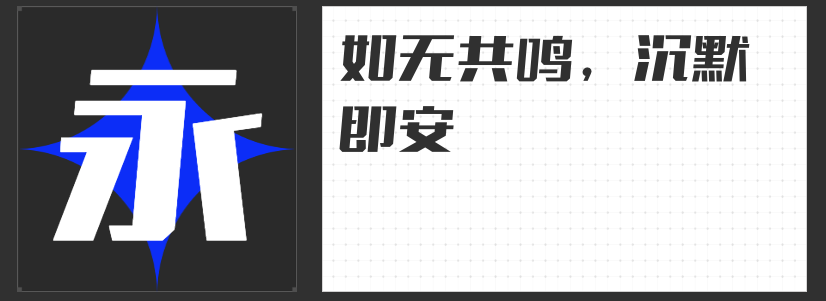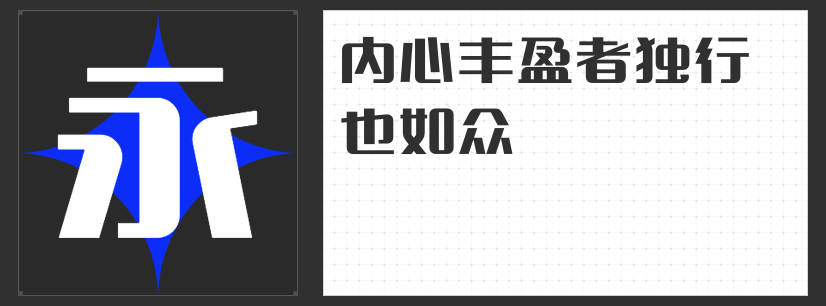
大暑节气设计字体推荐:四款风格化字库打造视觉盛宴
大暑作为二十四节气中最炽热的篇章,其设计需兼顾传统韵味与现代张力。以下四款专业字库字体,以独特风格诠释节气内涵,助力设计师在海报、包装、数字媒体等领域精准传递大暑的热烈与诗意。
一、字恋狂风摇简 粗体
这款字体以“被风吹过的文字”为设计理念,笔画如摇曳的草叶般自然弯曲,字型比例失衡却充满动态平衡感。其手写质感与大暑的“自然生命力”主题高度契合,尤其适合用于节气主题插画、儿童绘本或手作品牌宣传。例如,在“大暑·荷风送香”主题海报中,用该字体书写标题,配合水彩荷花背景,可营造出“风动荷香”的沉浸式视觉体验。
二、高手庆科乖乖体 大黑
以直线与圆角构建的几何字型,既保留黑体的理性秩序,又通过布白均匀与重心平稳传递清凉感。其横细竖粗的笔画对比,搭配竖弯钩的简洁处理,使长文案排版更显通透。在饮品包装设计中,用该字体呈现“大暑冰饮节”主题,搭配冷色调渐变背景,可强化“解暑降温”的产品卖点,同时提升信息识别效率。
三、高手庆科冷酷体 大黑
这款字体以5度倾斜与笔画切割设计打破传统黑体框架,钩笔画斜切处理与西文字符的切角倾斜形成视觉统一,传递出强烈的未来感。适用于科技品牌的大暑营销活动,如智能家电“极暑挑战赛”海报,用冷酷体书写“40℃高温,我自岿然不动”标语,搭配金属质感背景,可凸显产品耐高温性能,同时塑造品牌硬核形象。
四、云书法永刚漆书体
源自清代金农“漆书”风格的再创作,这款字体以扁笔刷墨的厚重笔画与棱角分明的结构,复刻碑帖的金石意趣。其乌黑如漆的墨色与大暑“伏茶”“晒伏”等传统习俗形成文化呼应,适合用于非遗展览、文化纪录片标题设计。例如,在“大暑·古法晒书”活动主视觉中,用漆书体书写“千年文脉,一晒传承”,搭配宣纸纹理背景,可深化观众对节气文化厚度的感知。
四款字体从自然、现代、科技、文化四个维度解构大暑,为设计师提供多元化的表达工具。选择时需结合品牌调性与传播场景,让字体成为节气叙事的无声主角。